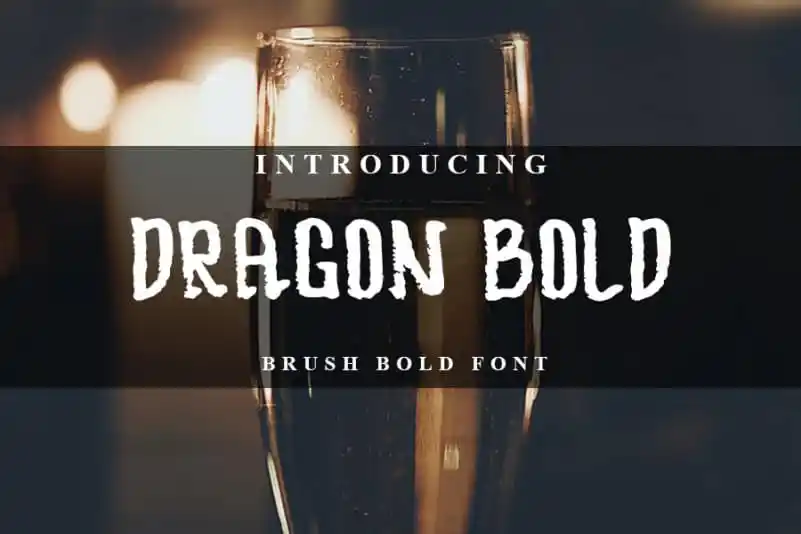
DRAGOON BOLD Display Font – Download Grátis
A DRAGOON BOLD Display Font é uma escolha perfeita para designers atentos aos detalhes que desejam imprimir um ar sofisticado e clássico, sem abrir mão de uma aparência contemporânea e atual. Esta fonte brush mantém suas influências do escritório tradicional, mas também oferece uma sensação moderna e fresca, o que a torna uma opção versátil e atraente para um vasto leque de ideias criativas. Este design elegante é especialmente adequado para aplicações como cartões de visita, títulos e material de embalagem, proporcionando aos designers a oportunidade de dar um toque pessoal e único em suas produções. Com DRAGOON BOLD Display Font, sua mensagem ganha vida com esse estilo único e reconhecível.